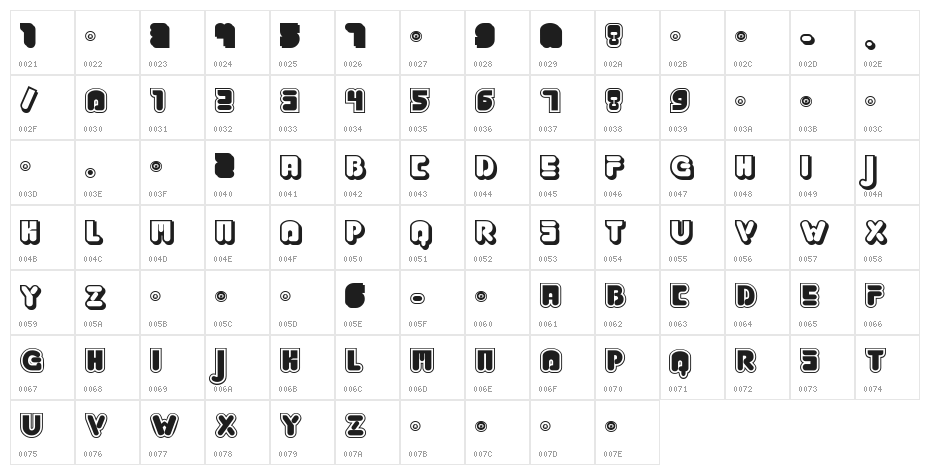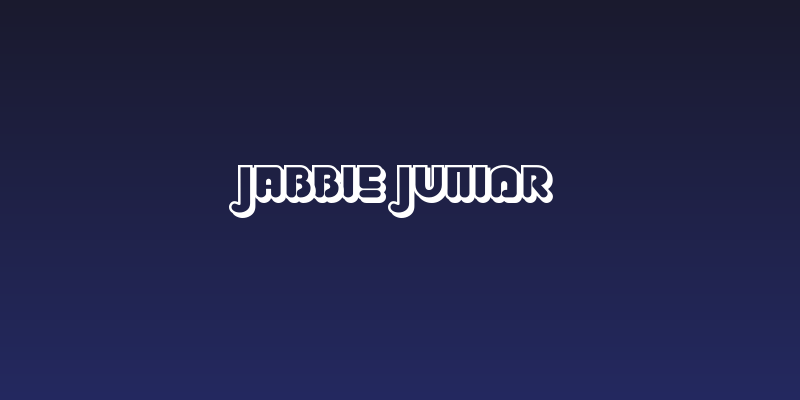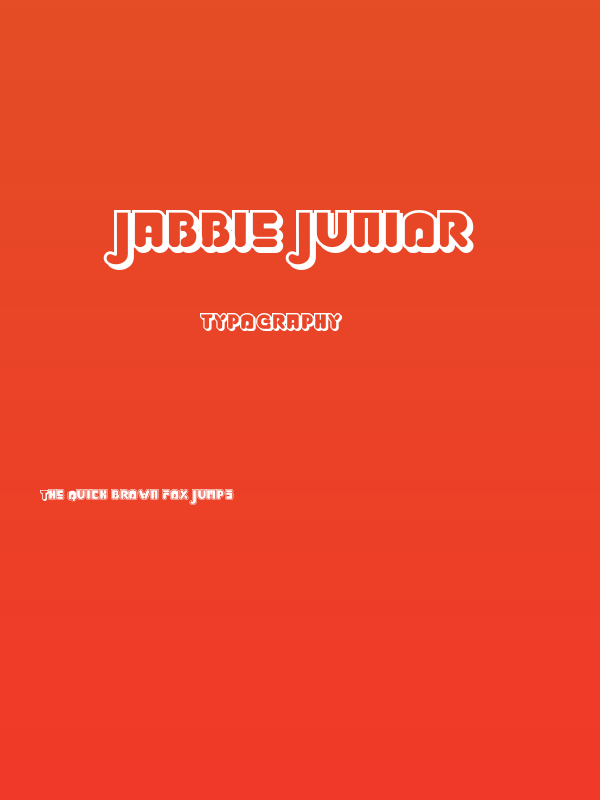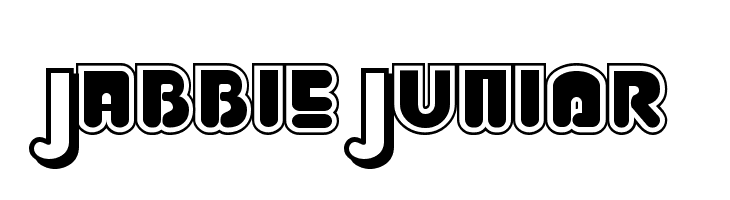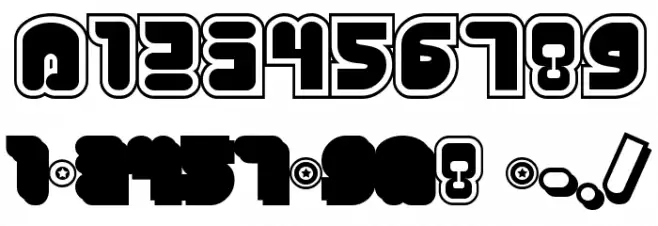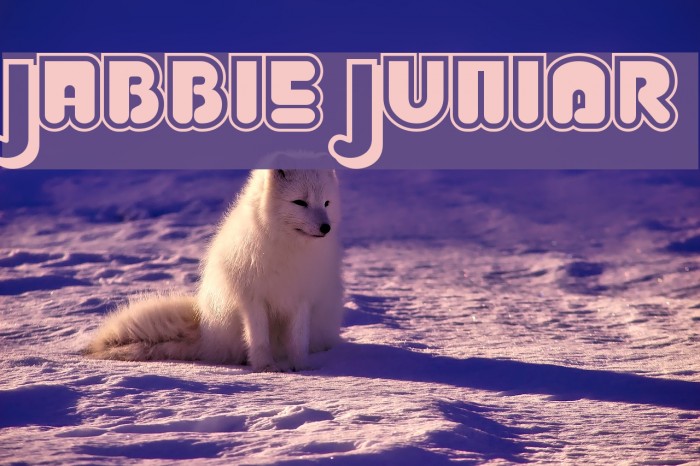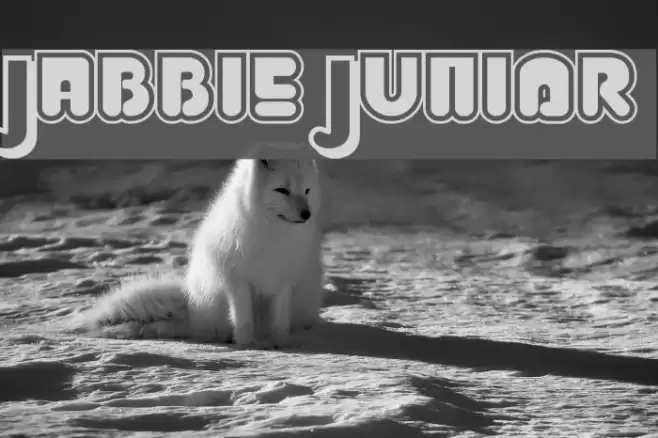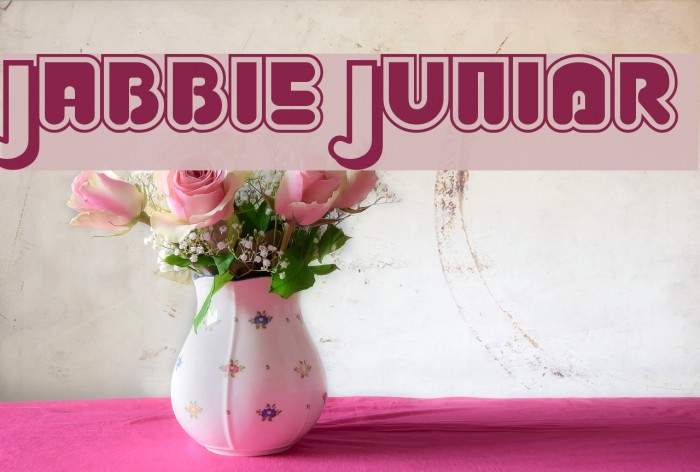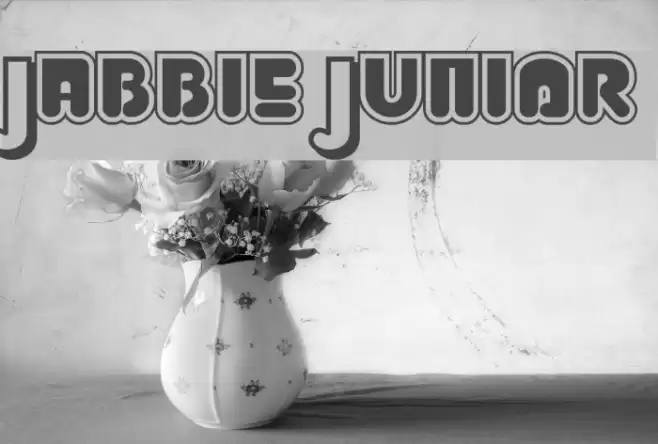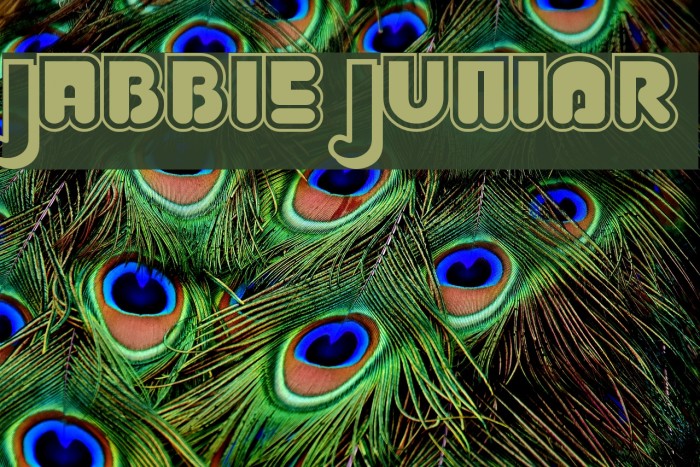
Jabbie Junior Font
✎ Decorative
| Категория | Decorative |
| Общий стиль | Playful, Modern |
| Рекомендуемые проекты | Ideal for children's books, playful branding, posters, and creative advertising campaigns. |